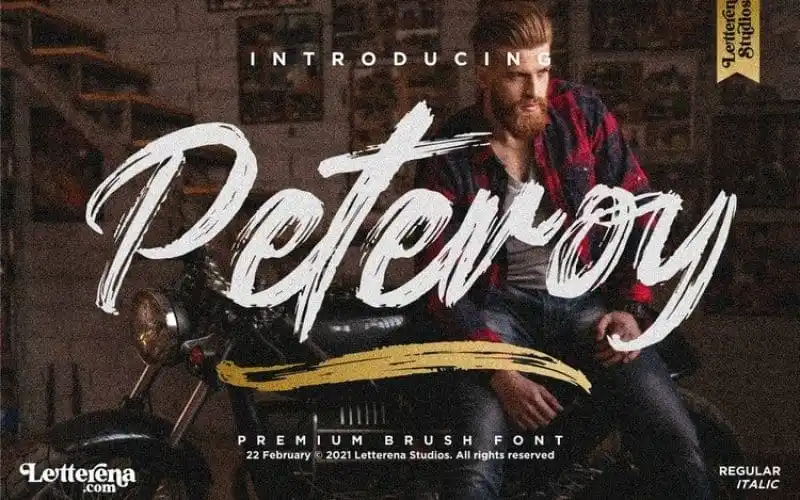
Peteroy Brush Font – Download Grátis
A Peteroy Brush Font é uma fonte de letras cursivas com traço de pincel desenvolvida pelo Letterena Studios para projetos urbanos contemporâneos. Com seu belo estilo de escrita à mão e textura única de pincel, esta fonte é ideal para um leque amplo de aplicativos, desde logomarcas e projetos de marca até etiquetas e camisetas personalizadas. Suave e elegante ao mesmo tempo, ela se adapta perfeitamente a várias aplicações digitais e impressivas, seja em design de móveis ou em arte para produtos de embalagens, capas de livros, cartões de nome, convites, encomendas e até na estampa de fotografias. Com uma forte personalidade gráfica que complementa qualquer projeto, a Peteroy Brush Font se destaca como um recurso essencial para quem busca estilo arquitetônico moderno em sua próxima criação visual.